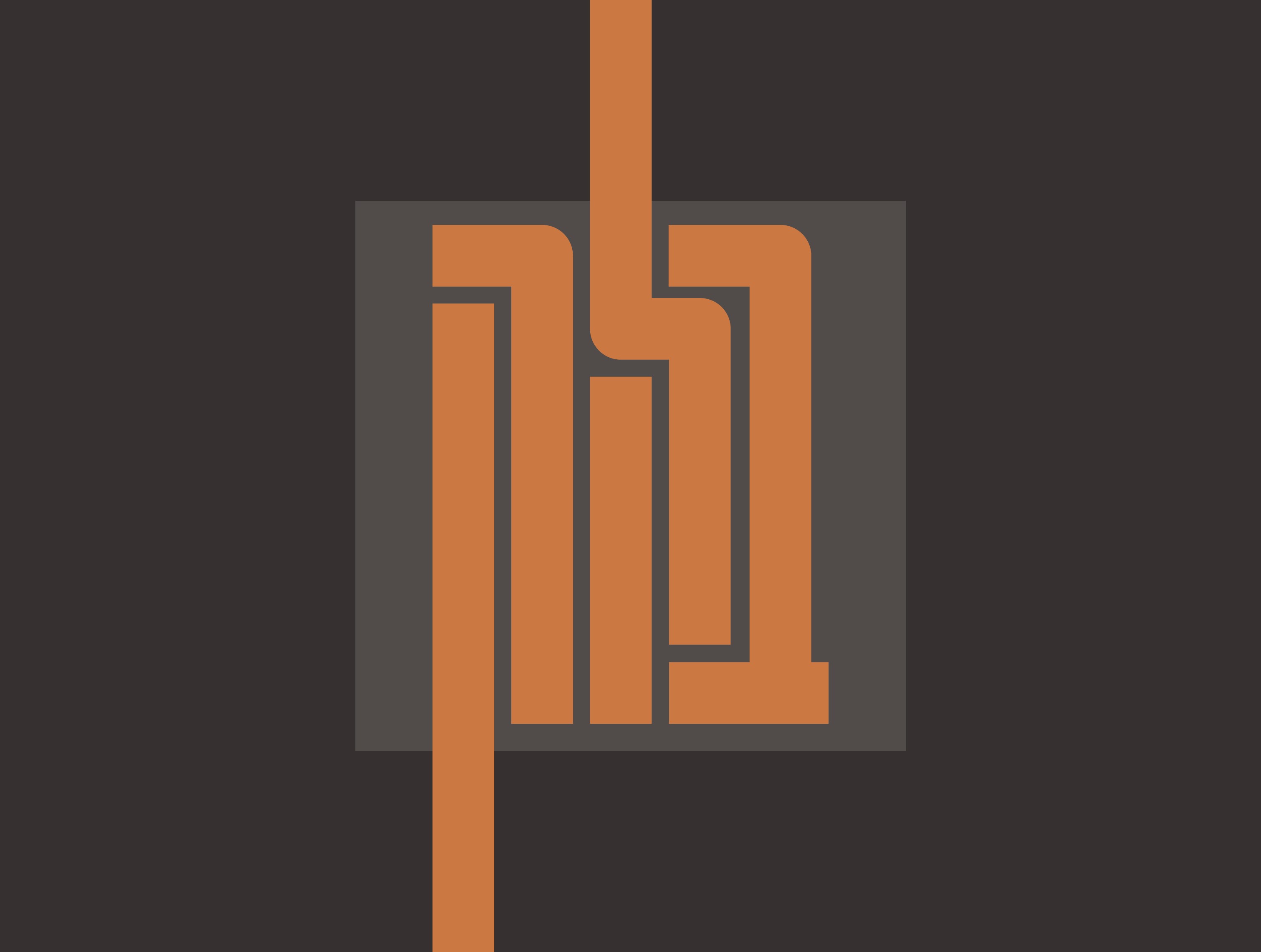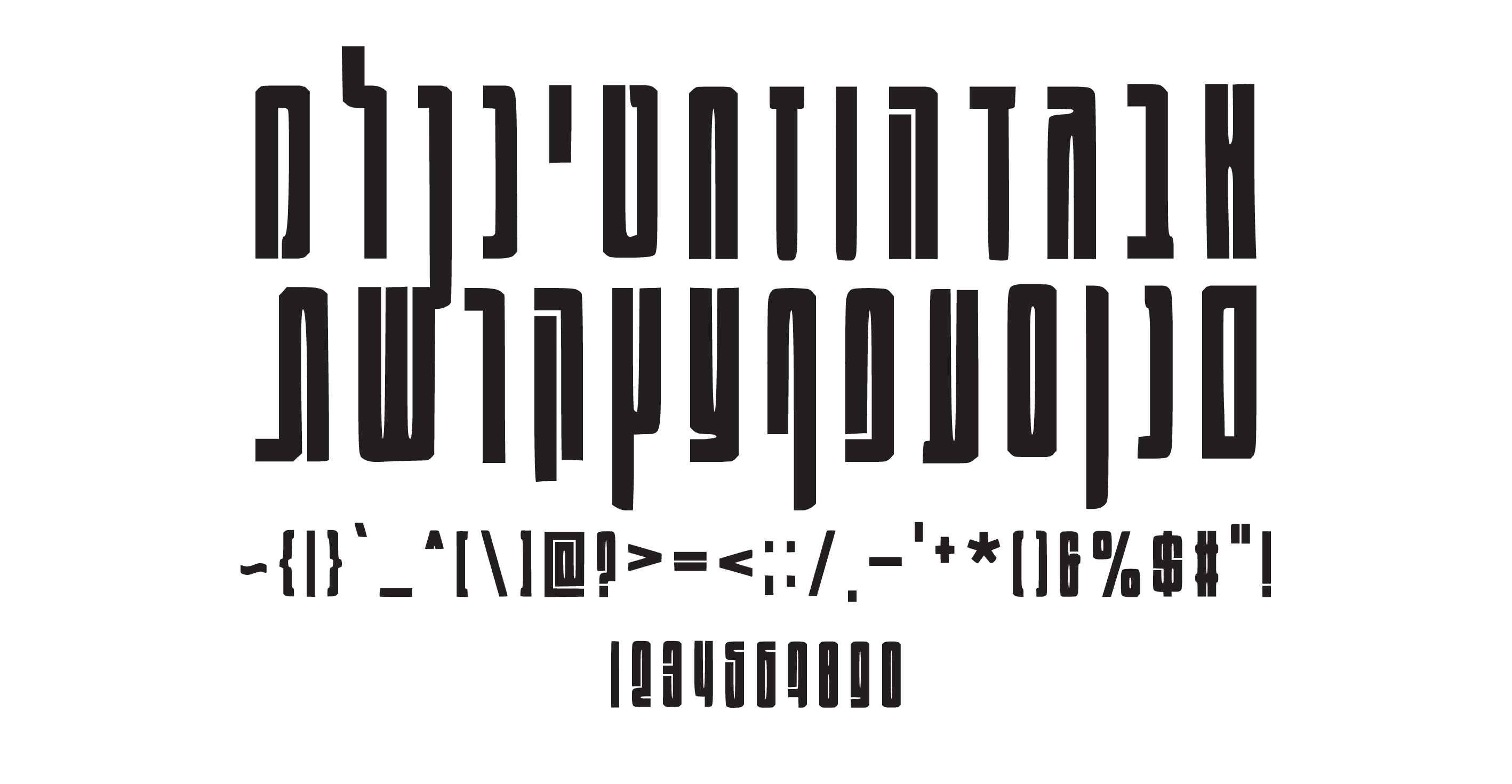
פונט בלוק
פונט עברי גאומטרי, דחוס ועוצמתי, מושלם לפוסטרים, לוגואים וכותרות מודגשות.
בלוק — הפונט שלא מתנצל
יש פונטים שמזמינים אותך בעדינות, ויש כאלה שפשוט שוברים את הדלת ונכנסים.
בלוק הוא פונט עוצמתי, גאומטרי ומסודר, שלא פוחד לתפוס מקום.
כל אות בפונט הזה היא גוש עיצובי בפני עצמה — עם קווים חדים, זוויות נוקשות ודחיסות מרשימה, הוא נותן תחושה של כוח, נוכחות, ושליטה מלאה בשטח.
הפונט הזה מושלם לכל מי שמחפש לגרום לטקסט לקפוץ החוצה ולהפוך לאלמנט גרפי בפני עצמו.
איפה הוא מרגיש בבית?
🔸 פוסטרים נועזים
🔸 לוגואים חזקים ובועטים
🔸 עטיפות אלבומים ועיצובים אורבניים
🔸 כותרות דרמטיות שמבקשות תשומת לב מיידית
למי הוא מתאים?
למעצבים נועזים, מותגים עם אופי חזק, וכל מי שמחפש להצהיר אמירה ברורה וחדה.